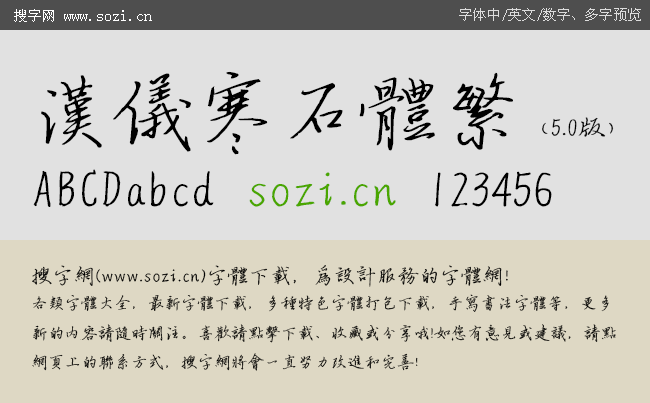
漢儀寒石體繁
搜字網(wǎng)提供一款漢儀寒石體繁中文字體下載,漢儀伊寧隸寒石體,漢儀寒石體是介于楷書(shū)、草書(shū)之間的一種書(shū)體,可謂之為行書(shū)。在書(shū)寫(xiě)時(shí),不乏楷書(shū)的端莊、穩(wěn)重,同時(shí)又不失草書(shū)的飄逸、灑脫。用筆簡(jiǎn)捷、干練,行云流水;字形意態(tài)活潑,姿態(tài)優(yōu)美,令人賞心悅目。該字體,規(guī)范、美觀,易于辨認(rèn)。適用于廣告設(shè)計(jì)、平面設(shè)計(jì)、印刷包裝、藝術(shù)設(shè)計(jì)、網(wǎng)站設(shè)計(jì)領(lǐng)域。